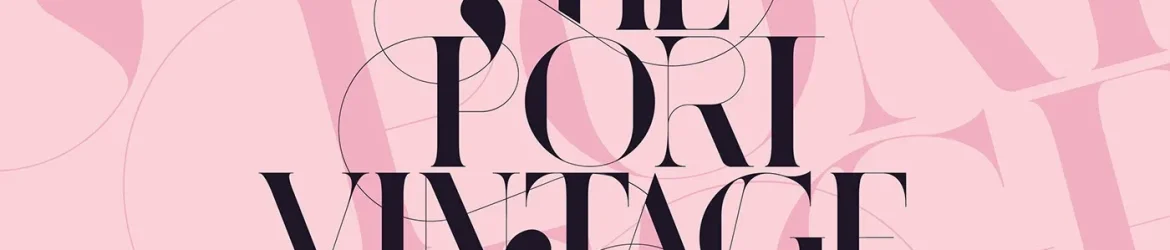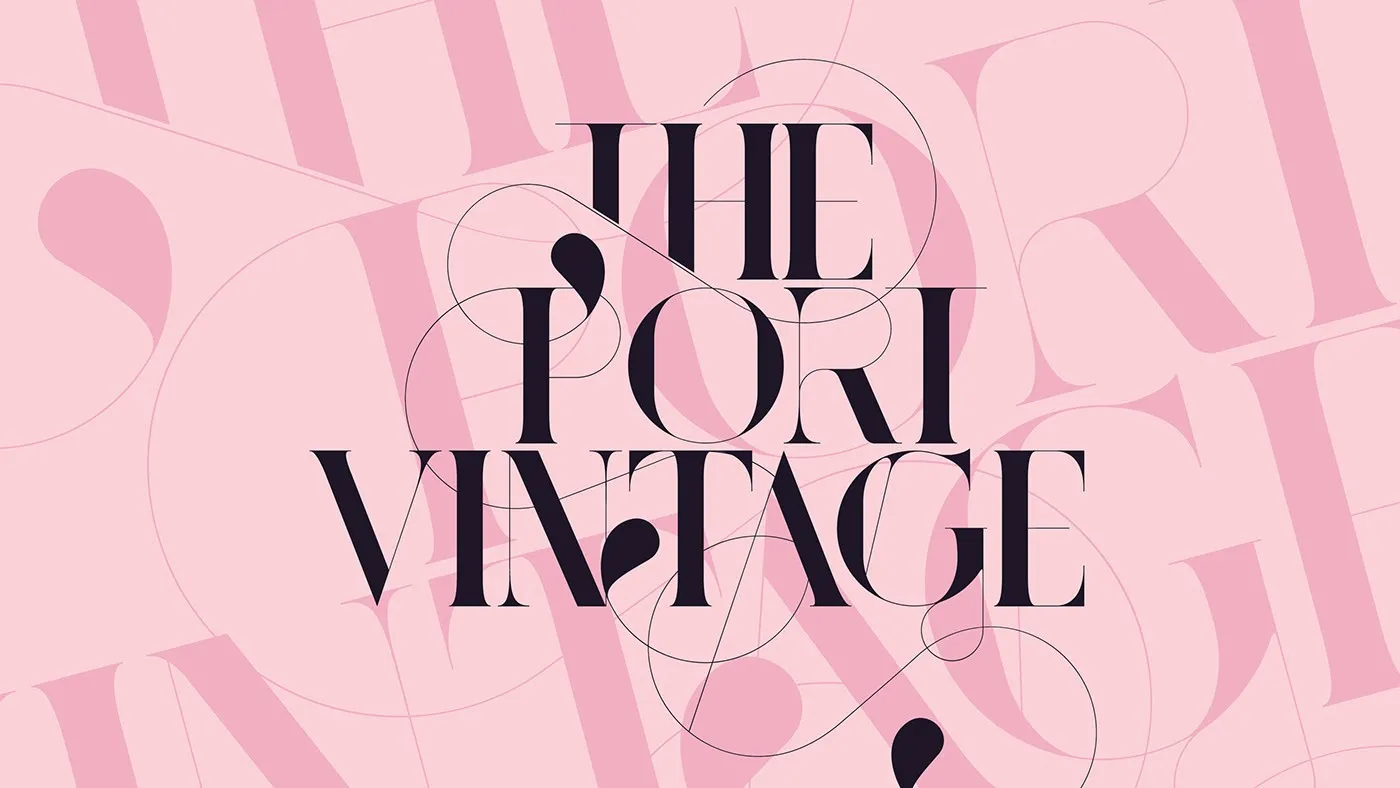
Port Vintage Font Family
A ‘Port Vintage Font Family’ é uma bela serifada inspirada nos clássicos do tipo Didone. Inspirada nas obras icônicas dos mestres de tipografia, como Bodoni e Didot, também captura a vitalidade e elegância da arte do desenho à mão, num estilo geométrico e moderno. Esta fonte oferece um toque vintage para qualquer projeto gráfico, seja em logotipos, rótulos ou até mesmo embalagens. Suas linhas firmes e arquitetônicas dão uma aparência sofisticada a qualquer texto, enquanto seu design geométrico proporciona o aspecto moderno que tanto os designers procuram para seus projetos atuais. Uma fonte perfeita para quem quer trazer um toque de elegância vintage sem perder a atualidade.